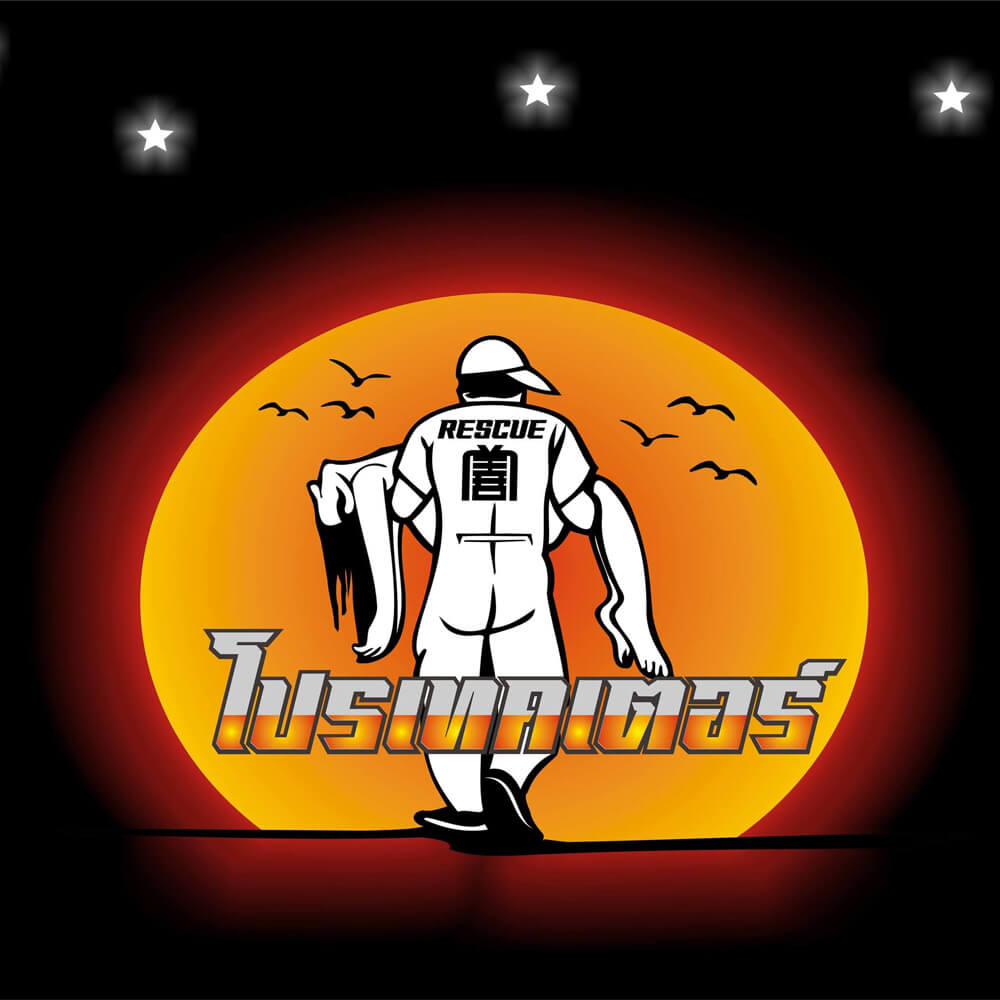
เอสดี มาสเตอร์พีซ (sd masterpiece)
เอสดี มาสเตอร์พีซ เป็นฟอนต์ออกแนว Modern Classic ผสมผสานแนว Vintage ตอนแรกตั้งใจจะทำเฉพาะ ภาษาอังกฤษเช่นเดียวกับ sd best in class แต่ทำไปทำมาเลยเติมภาษาไทยมาด้วย เผื่อมีคนชอบแนววินเทจบ้าง
ฟอนต์ เอสดี แรงเวอร์ เป็นฟอนต์ที่ได้แรงบันดาลใจจาก เครื่องดื่ม แรงเวอร์ พอดีเดินเข้าไปในร้านสะดวกชื้อเห็นมีเครื่องดื่มหลายชนิด แต่ไปสะดุดตรงยี่ห้อพอดี เลยนำมาต่อยอดเป็นตัวอักษรทั้ง 44 ตัว ทำเป็นฉบับเต็มขึ้นมา นำมาแบ่งปันให้เพื่อนๆ ในสายงานกราฟิก ห้างร้าน บริษัท องค์กร และหน่วยงานอื่นๆ ที่ต้องการนำตัวหนังสือไปใช้ในการสร้างสรรค์ผลงานของตัวเองได้ใช้กัน
เอสดี ไฟท์เตอร์ เป็นฟอนต์ที่ได้แรงบันดาลใจจากโฆษณารถโตโยต้า รีโว ซึ่งมีข้อความ “ตัวตนของฅนจริง” เลยอยากจะทำเป็นฟอนต์ขึ้นมา รูปร่างฟอนต์ ออกแนวเหลี่ยมๆ ดูแข็งแกร่งมีพลังดี นำมาให้เพื่อนๆ สายงานกราฟิก และหน่วยงานอื่นๆ ได้ใช้กัน
เอสดี การ์ตูน2 เป็นฟอนต์ที่ต่อจาก เอสดีคอมมิค หลังจากที่ทำฟอนต์แนวซิ่งๆ มาแจกหลายฟอนต์แล้ว ฟอนต์นี้ออกแนวตัวมน กลมๆๆๆ ดองไว้นานมากฟอนต์นี้ นำมาให้เพื่อนๆ ในสายงานกราฟิก และหน่วยงานอื่นๆ ได้ใช้กัน
เป็นฟอนต์ที่ต่อจากเวอร์ชัน 1 ที่มีแต่ภาษาไทย มาเพิ่มเติมภาษาอังกฤษตอนหลังและปรับเปลี่ยนตัวอักษรภาษาไทยบางตัว นำมาให้เพื่อนๆทุกท่านทั้งสายงานกราฟิก และสายอื่นๆ นำไปใช้กัน
SD Performance (เอสดี เพอร์ฟอร์แมนซ์)
เป็นฟอนต์แนวซิ่งๆๆ เหมือนเดิมครับ เหมาะสำหรับยุคที่การแต่งรถด้วยสติ๊กเกอร์กำลังเป็นที่นิยมในกลุ่มวัยรุ่น
หลังจากที่มีโอกาสได้ปล่อยฟอนต์ตัวแรกไปแล้ว ฟอนต์นี้เป็นฟอนต์ที่สองครับมีชื่อว่า เอสดี ฮอลล์ ได้แนวคิดมาจากลูกอมฮอลล์